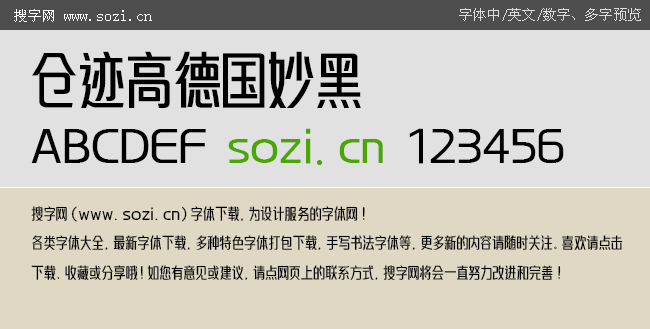
倉(cāng)跡高德國(guó)妙黑
搜字網(wǎng)給大家提供一款倉(cāng)跡高德國(guó)妙黑中文字體下載,倉(cāng)跡高德國(guó)妙黑由倉(cāng)跡字庫(kù)的設(shè)計(jì)師高德國(guó)設(shè)計(jì),妙黑體高挑時(shí)尚,寬實(shí)粗壯,既適合品牌設(shè)計(jì),也可做廣告標(biāo)題。獨(dú)特的高挑結(jié)構(gòu),讓字體充分結(jié)合了字形與創(chuàng)意,在眾多行業(yè)場(chǎng)景均有上乘表現(xiàn)。免費(fèi)供大家使用。適合應(yīng)用于藝術(shù)設(shè)計(jì)、平面宣傳設(shè)計(jì)、網(wǎng)頁(yè)設(shè)計(jì)、海報(bào)設(shè)計(jì)等應(yīng)用。